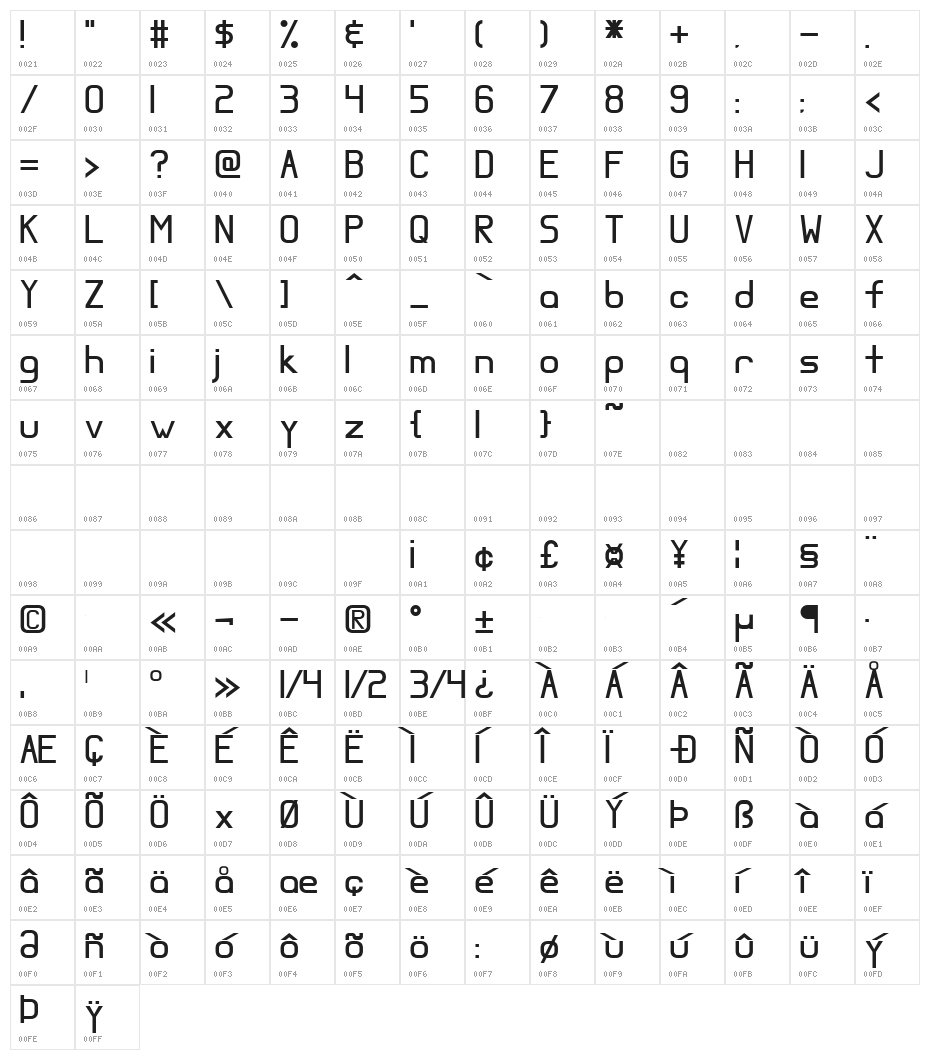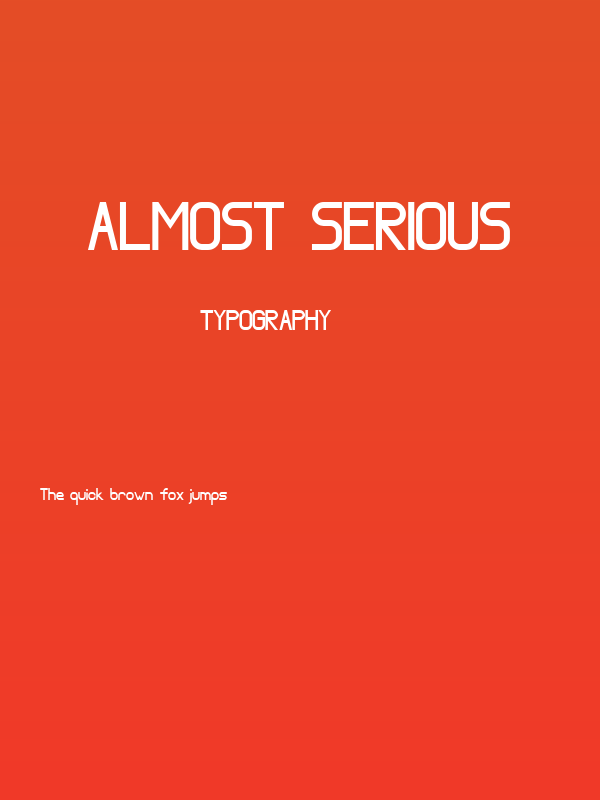
Almost Serious Font
| Caz de utilizare | Headlines, Logos, Digital Media |
| Proiecte propuse | Ideal for branding, advertising, and digital media projects that require a modern and clean aesthetic. |